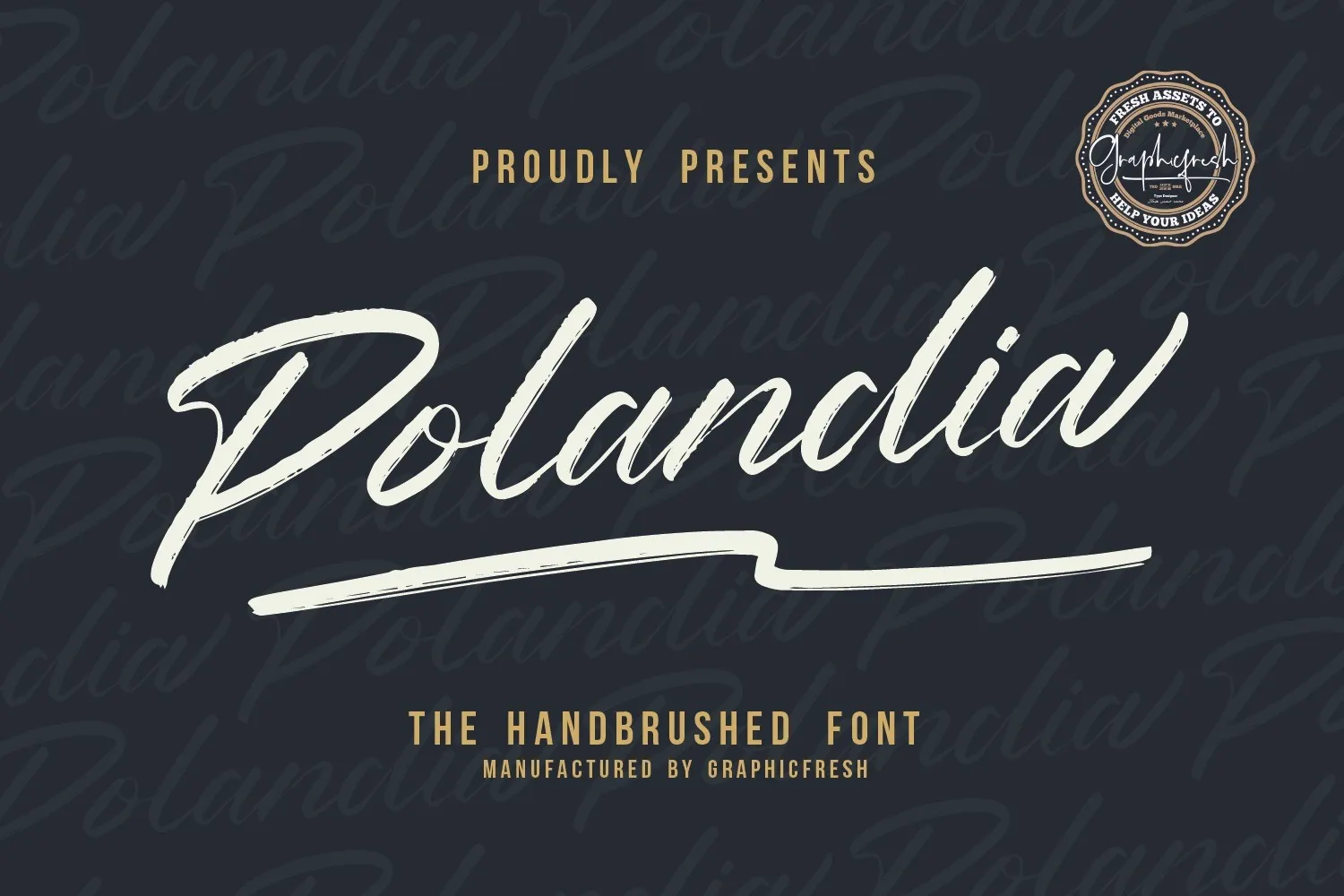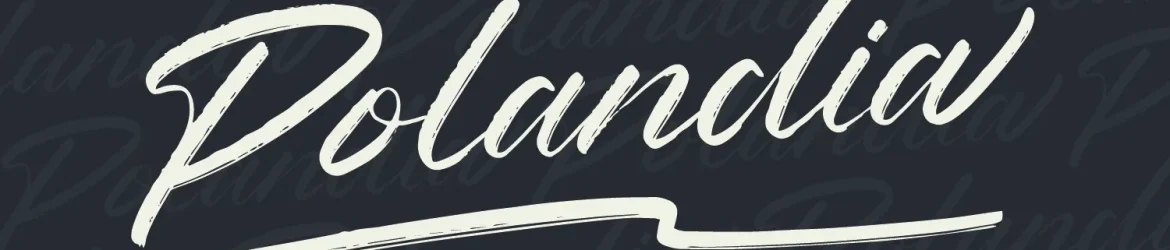
Afont Polandia é uma bela fonte brush script criada pela Graphicfresh com um estilo elegante de caligrafia. Ela vem equipada com um estilo moderno e elegante que se destaca perfeitamente para qualquer design. Ideal tanto para branding, convites de casamento, revistas, têis personalizados, cartões de visitas, citações e até mesmo postais, esta fonte é uma escolha atraente para todos aqueles que buscam um toque único em suas criações gráficas. Seja você um designer profissional ou iniciante, Polandia oferece o que há de melhor na categoria das fonts script, tornando-a a escolha perfeita para qualquer projeto.